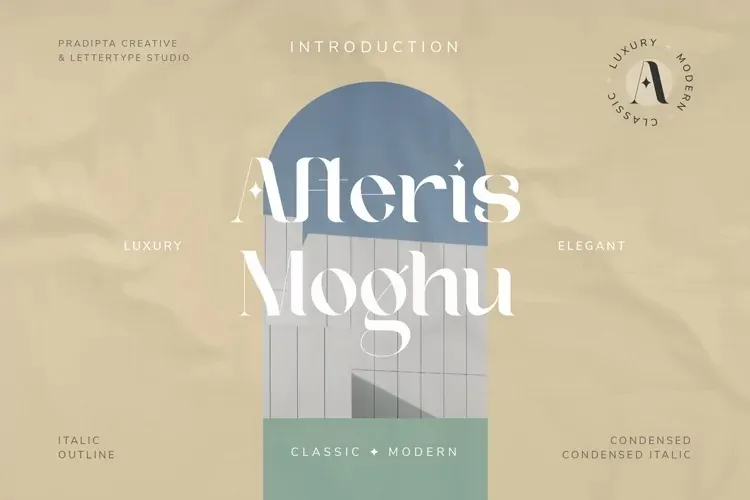
Afteris Moghu Font – Fonte Grátis
Afteris Moghu Font
A fonte Afteris Moghu oferece uma experiência visual elegante e sofisticada para projetos que exigem um toque tradicional e refinado. Criada pela Pradipta Creative, esta serif é perfeita para diversos aplicativos, desde identidades de marca e vestuário até cartazes e convites para casamentos. Sua beleza natural e seu movimento vintage dão uma aparência elegante a qualquer projeto, tornando-a uma escolha ideal não apenas para logotipos e elementos visuais, mas também para criações gráficas que buscam um ar sofisticado e estilizado. Engane-se ao imaginar este estilo delicado; ele pode ser encontrado em uma ampla variedade de materiais, desde roupas até cartazes e convites para eventos especiais. A fonte Afteris Moghu é o elemento perfeito para aqueles que desejam dar um toque único e sofisticado a qualquer projeto gráfico.